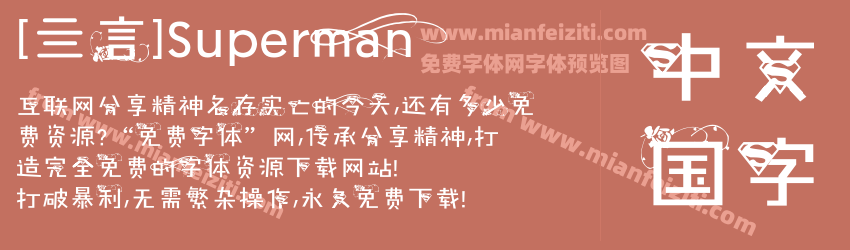
![[亖言]Superman [亖言]Superman](https://mimg.cdn.bcebos.com/upload/fontimgs/cover_ogimage/cover_ogimage_205118.png?auth_key=1763074600-0-0-b5e55346474adc9a7cd11beb6427260e)
本款“[亖言]Superman”是一款书写很新颖的字体,字体大方,适合各种设计作品使用!欢迎下载!